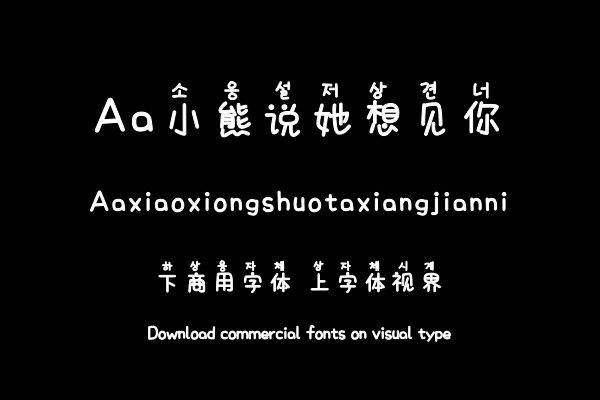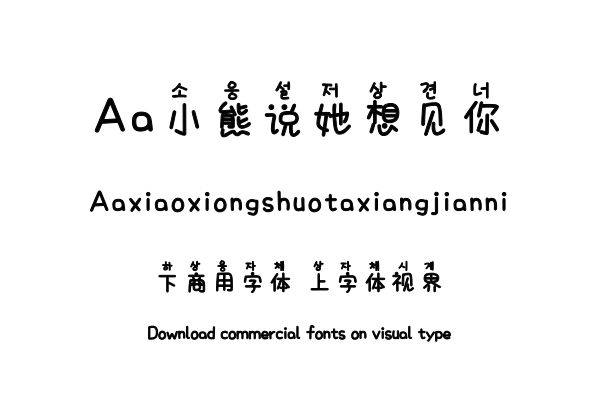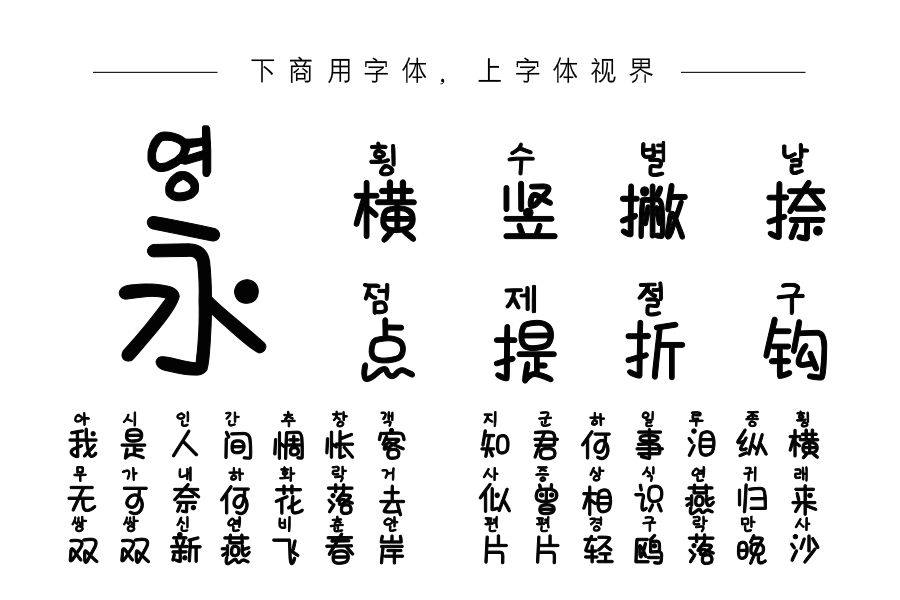
以字体“奶油熊熊”为打底字的韩文字幕字体,创意性与实用性并存,适用场景广泛。购买须知:“下载服务费”与“字体VIP”所获得字体 仅用于个人非商用, 商用请联系付费授权。本字体为电脑用字,手机没有root权限不支持直接手机换字(手机如何root,请自行百度搜索教程)。购买前请先 了解清楚后再付款 ,字体为虚拟产品无法回收 一旦购买不支持退款。